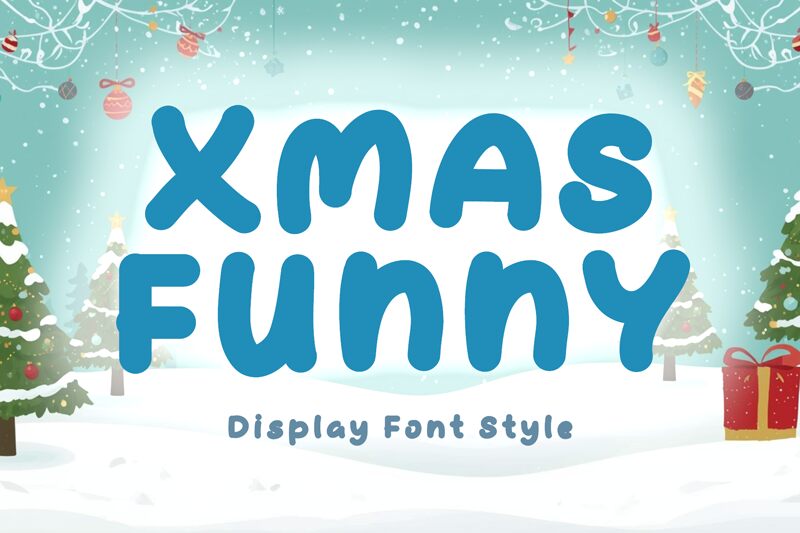
Xmas Funny Demo
Xmas Funny é uma fonte display cartoon gratuita com letras arredondadas, estilo bolha, e curvas suaves e cheias. As formas parecem desenhadas à mão e informais, com um ritmo solto que mantém o conjunto todo com um visual amigável, nada rígido.
A Xmas Funny funciona muito bem em cartões de natal, pôsteres infantis, convites de festa, etiquetas de produtos, artes para redes sociais e logotipos curtos, pois os caracteres permanecem expressivos e fáceis de usar. Esta fonte gratuita traz um toque cômico leve a embalagens sazonais, títulos divertidos, adesivos e qualquer trabalho de lettering onde um estilo arredondado e informal é essencial.